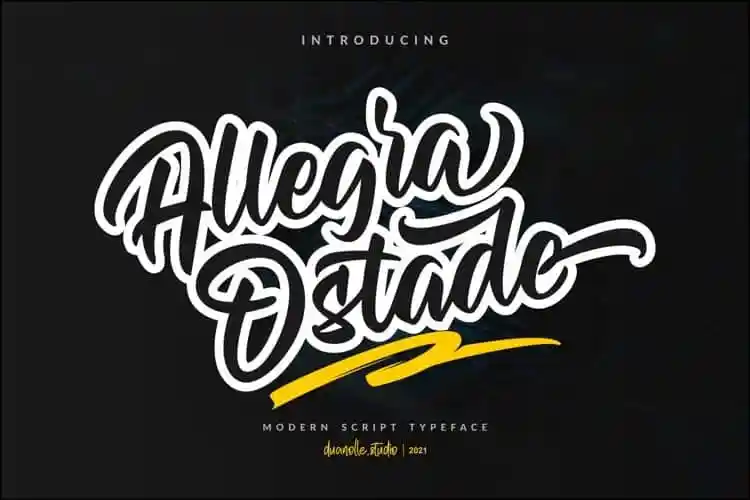
Allegra Ostade Bold Script Font – Download Grátis
A Allegra Ostade Bold Script Font é uma fonte tipográfica elegante para quem busca um visual delicado e flutuante. Desenvolvida pela Duanolle Studio, esta fonte script é perfeitamente adequada tanto para criações profissionais quanto para produzir design gráfico de alto nível. Ela oferece muitas alternativas diferentes que permitem uma ampla gama de opções para os projetos mais variados. Esta fonte é especialmente divertida e versátil, pois você pode adaptar cada palavra ao seu projeto. É perfeita tanto para logotipos quanto para materiais de marca, infográficos ou qualquer tipo de design que deseje dar um toque único. Não hesite em explorar as infinitas possibilidades com esta fonte elegante e sofisticada.